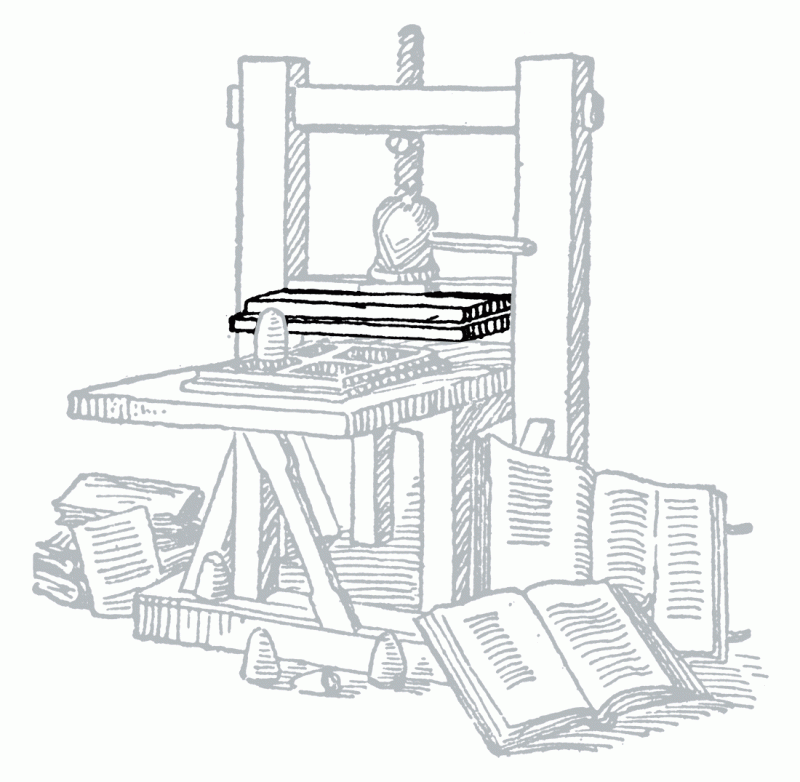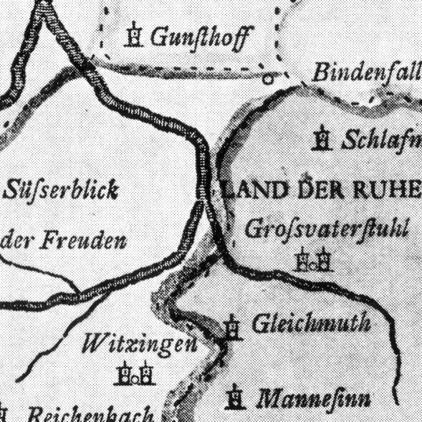
Werden Proportionale Ziffern in Tabellen eingesetzt, ergibt sich durch die teils deutlich unterschiedliche Breite der Ziffern ein sehr unruhiges Satzbild. Sollen alle Ziffern stets exakt untereinander stehen, benutzt man deshalb (wenn verfügbar) Tabellensatzziffern. Bei diesen Ziffern ist die Dickte der Ziffern exakt gleich. Sind die verschiedenen Ziffernarten auf verschiedene Schriftschnitte verteilt, erkennt man die tabellarischen Versalziffern meist an dem Zusatz »TF« (für Tabular
Ein Taschenbuch ist heute ein kleinformatiges, handliches Buch, das zu einem relativ niedrigen Preis in oft hohen Auflagen erscheint. Umschlag und Bindung sind in der Regel wie bei einer Broschur (»Softcover«) ausgeführt. Ein Taschenbuch ist also gleichzeitig auch eine Broschur, aber nicht jede Broschur auch ein Taschenbuch.
Siehe Manuskripthalter
Im Grafikdesign ist es üblich, Schriftgrößen direkt spezifische Einsatzbereiche zuzuweisen. So gelten etwa Schriftgrößen von 10 bis 12 Punkt als angenehme Lesegrößen für Fließtexte. Jedoch bezieht sich so eine Zuordnung immer nur auf Drucksachen, die man in die Hand nehmen kann und bei denen man daher von einem einigermaßen festen Leseabstand ausgehen kann. Aber selbst die großen Schriftgrade von Überschriften in einem Magazin können auf einem Schild viel zu klein sein, weil der Leseabstand gege
Der Tiegel ist der flache Gegendruckkörper in Maschinen für den Hochdruck nach dem Fläche-gegen-Fläche-Prinzip. Zu den Pressen mit Tiegeldruckprinzip zählen auch Spindel-/Schraubenpressen und Kniehebelpressen nach dem Stanhope-Prinzip. Fachsprachlich üblich ist jedoch die Beschränkung des Begriffs Tiegeldruckpresse (oder kurz »Tiegel«) auf Pressen mit Klapp-Tiegeln nach Boston-/Liberty-/Gally- und Gordon-System.
Wenn sich in einer Buchstabenform zwei Elemente in einem relativ geringen Winkel berühren, kann dies im Druck in kleinen Schriftgrößen dazu führen, dass die Druckfarbe an dieser Stelle physisch oder zumindest scheinbar zusammenläuft und einen unerwünschten Fleck bildet. Um dem entgegenzuwirken werden die Schnittpunkte an den betreffenden Stellen optisch offener gestaltet. Im Englischen wird dieser Einzug Ink Trap genannt. Im Deutschen gibt es bislang keinen allseits akzeptieren Begrif
Die Titelei bezeichnet die Seiten eines Buchs, die dem eigentlichen Inhalt vorangestellt sind. Teil der Titelei eines Buches können zum Beispiel sein: der Schmutztitel, das Frontispiz, die Titelseite auf dem Titelblatt, Impressum, Vorwort, Widmung und Inhaltsverzeichnis.
Die Titelseite ist formell korrekt die Vorderseite des Titelblattes in Druckwerken wie Büchern. Häufig werden Titelseite und Titelblatt jedoch auch synonym verwendet. Die Titelseite enthält den Titel des Druckwerkes und bei Büchern heute in aller Regel auch Angaben zu Autoren, dem Verlag sowie Publikationszeit und -ort. Bei Büchern ist die Titelseite Teil der Titelei.
Englische Bezeichnung für Barock-Antiqua; im Deutschen sind auch die Synonyme Bastarda bzw. Bastardschrift gebräuchlich, die darauf verweisen, daß die Barocken sowohl Merkmale der Klassizistischen als auch der Renaissance-Antiqua in sich vereinigen.
TrueType wurde von Apple in den späten 1980er-Jahren entwickelt. Vorausgegangen waren Streitigkeiten mit dem damals noch kleinen Unternehmen Adobe. Dieses Unternehmen hatte mit PostScript schon Mitte der 1980er-Jahre einen Standard der Druckvorstufe geschaffen, der bereits skalierbare Schriften enthielt. Da Apple aber nicht bereit war, einen so wichtigen Teil seines Betriebssystems gegen Lizenzgebühren in die Kontrolle eines anderen Unternehmens zu übergeben, entschied man sich, ein eigenes Schr
ttfautohint ist ein Programm von Werner Lemberg, mit dem man TrueType-Fonts mit einer automatisch generierten Bildschirmoptimierung versehen kann. Die Version 1.0 erschien am 22.3.2014. Weitere Informationen und Download unter http://www.freetype.org/ttfautohint/
Der Typengreif war ein im deutschsprachigen Raum verbreiteter Industriestaubsauger zum Einsatz in Druckereien mit Handsatz. Das Gerät wurde vom Stuttgarter Unternehmen Typengreif Apparatebau Wilhelm Bilek vertrieben. Im Wesentlichen funktionieren der Typengreif und vergleichbare Geräte anderer Hersteller wie herkömmliche Staubsauger. Den Unterschied macht der Aufsatz. Über den Schlauch liegt ein permanenter Sog an. Wird der Aufsatz in das Fach eines Setzkastens mit Bleilettern gehalten
Ein Typograf ist ein Spezialist auf dem Gebiet der Anwendung von Schriften. (Zu alternativen Bedeutungen siehe Ende dieses Artikels) Typograf Jan Tschichold Umgangssprachlich wird die Bezeichnung Typograf oft fälschlicherweise als Synonym für Schriftgestalter verwendet. Allerdings gestaltet nur der Schriftgestalter (englisch »Type Designer«) Schriftarten; der Typograf benutzt in der Regel vorgefertigte Schriften für seine grafischen Gestaltungen. Natürlich kann ein Gestalt